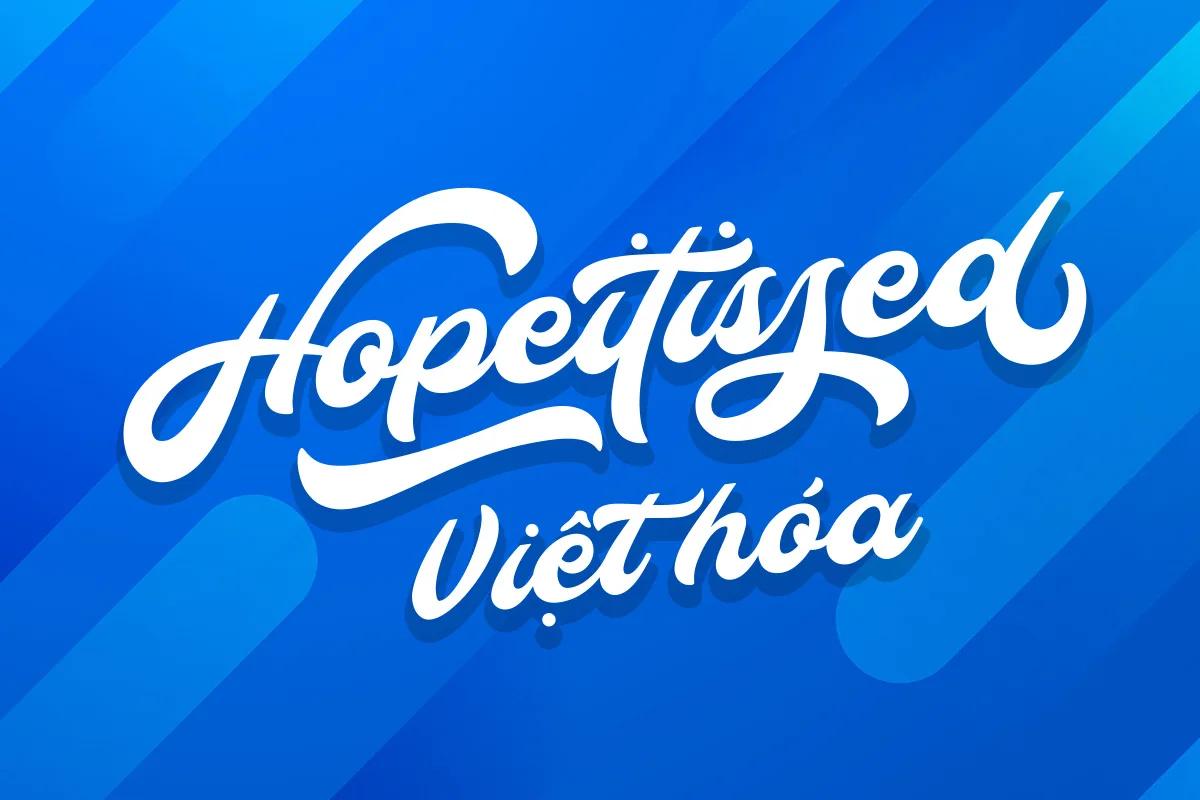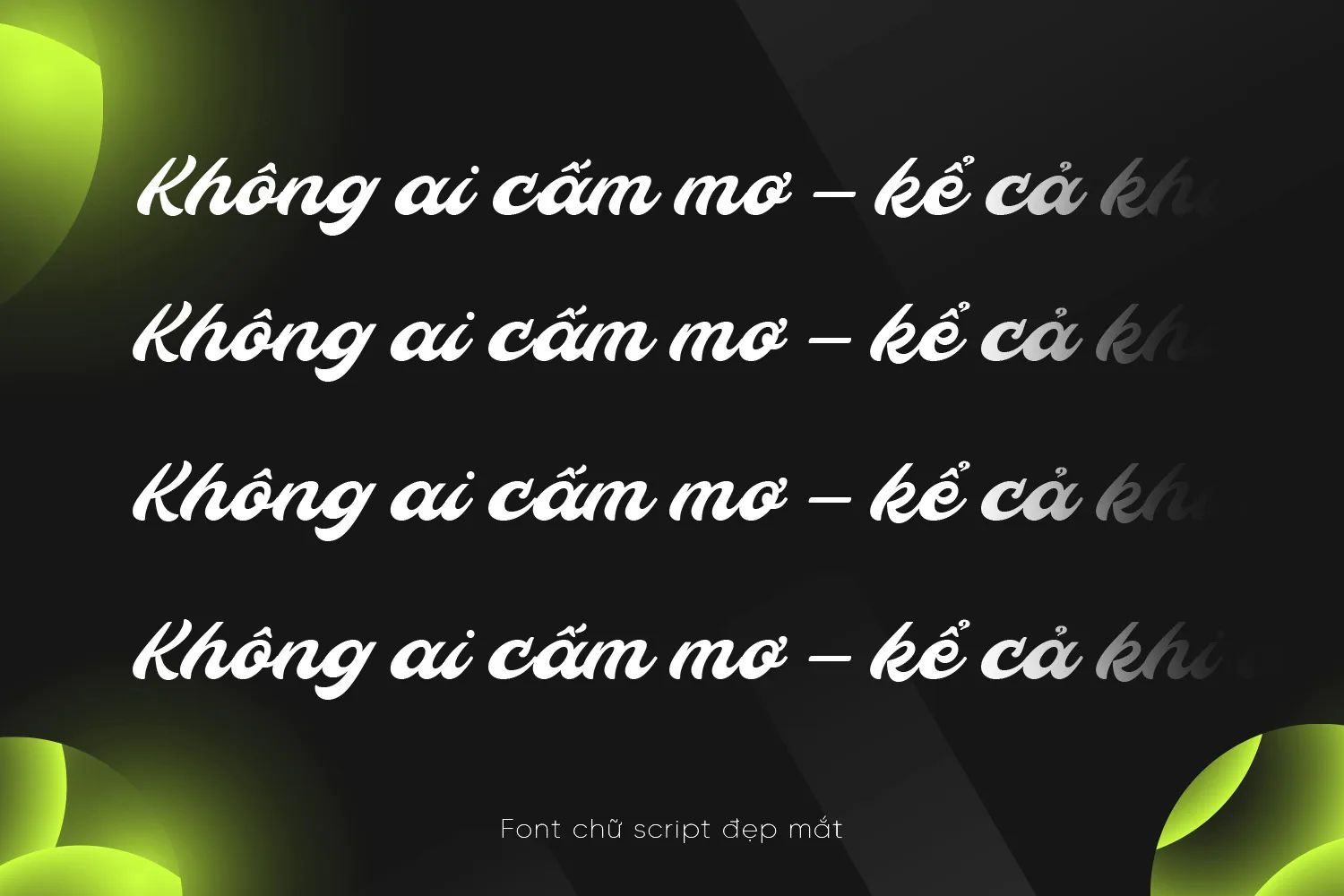
Hopeitissed Việt hóa – Nét chữ tay cho thế hệ sáng tạo
Hopeitissed là một font chữ script mang phong cách viết tay hiện đại, kết hợp giữa sự mềm mại và mạnh mẽ trong từng nét chữ. Phiên bản Việt hóa giữ trọn vẹn vẻ đẹp gốc với các đường cong uyển chuyển, độ nghiêng nhẹ cùng độ dày đều đặn, giúp tăng tính ứng dụng trong thiết kế. Font phù hợp với các dự án cần sự cá tính nhưng vẫn gần gũi như typography, thiệp mời, thiết kế thương hiệu cá nhân, sản phẩm sáng tạo hoặc tiêu đề nổi bật trên mạng xã hội. Các ký tự Việt được chau chuốt kỹ lưỡng, tương thích tốt với phong cách viết tay nguyên bản, đảm bảo sự hài hòa và dễ đọc.